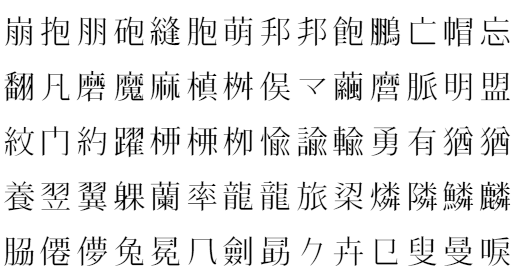
グリフウィキで制作していた Adobe-Japan1-4 の漢字グリフ(9138個)が完成したので、増加分を花園明朝OTに追加し、《花園明朝OT xProN R ver. 0.200》として公開した。
一般のProフォント・ProNフォントと同様に、いろいろな異体字を使うことができる*1。下の画像はその一部。異体字グリフは新しく作成したものが多いので、比較的バランスが整っているはず。どうでしょう?
普通のPro/ProNフォントは第3水準・第4水準・補助漢字のすべてを含んでいるわけではないが、この花園明朝OTは第3水準・第4水準・補助漢字をすべて収録している。ただし Adobe-Japan1-4 外のグリフについては字形のチェックをまだ行っていないため、小塚明朝の字形と異なるグリフも存在している。
今のところ「々〆〇仝」と漢字しか収録していないので、改変可能な他のフォントからアルファベットやら仮名やらを取り込みたいところ。